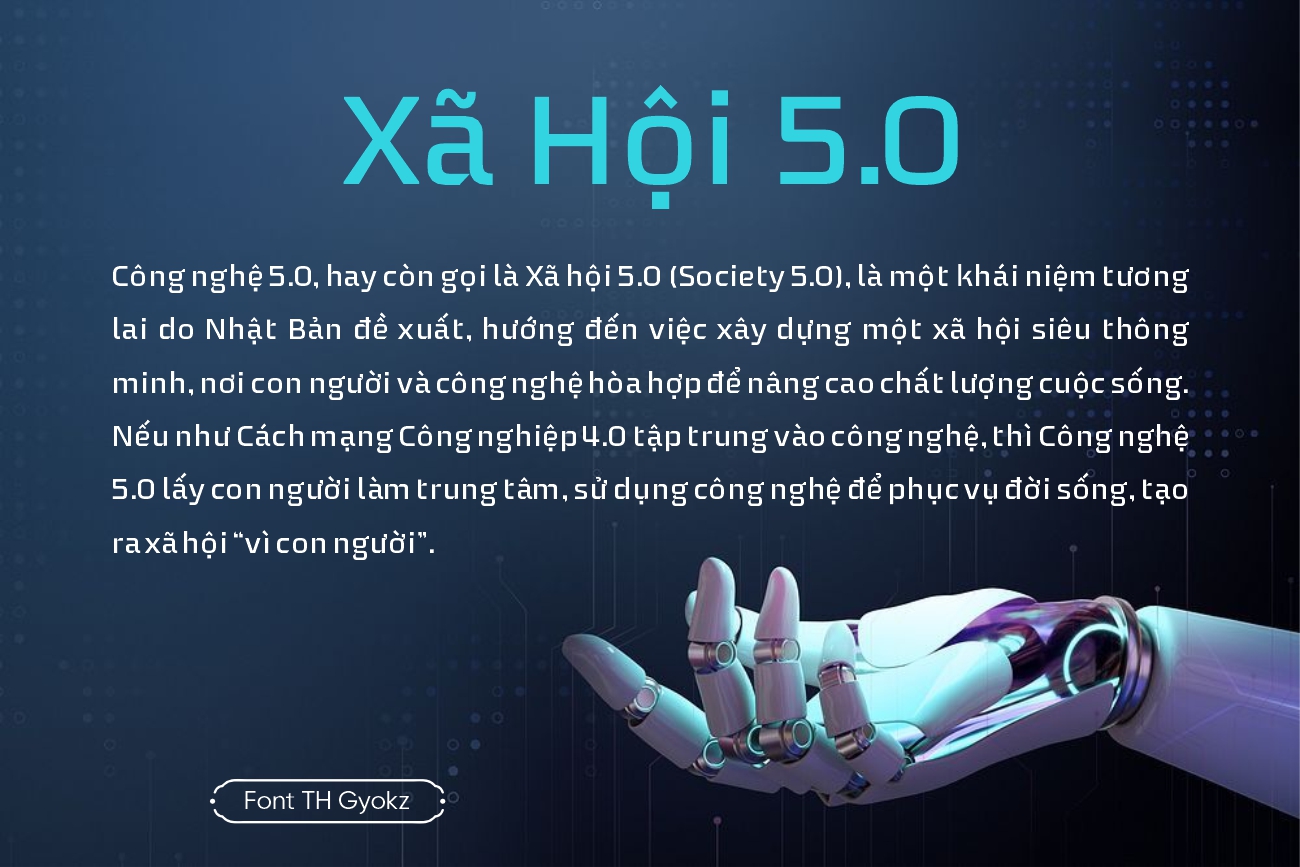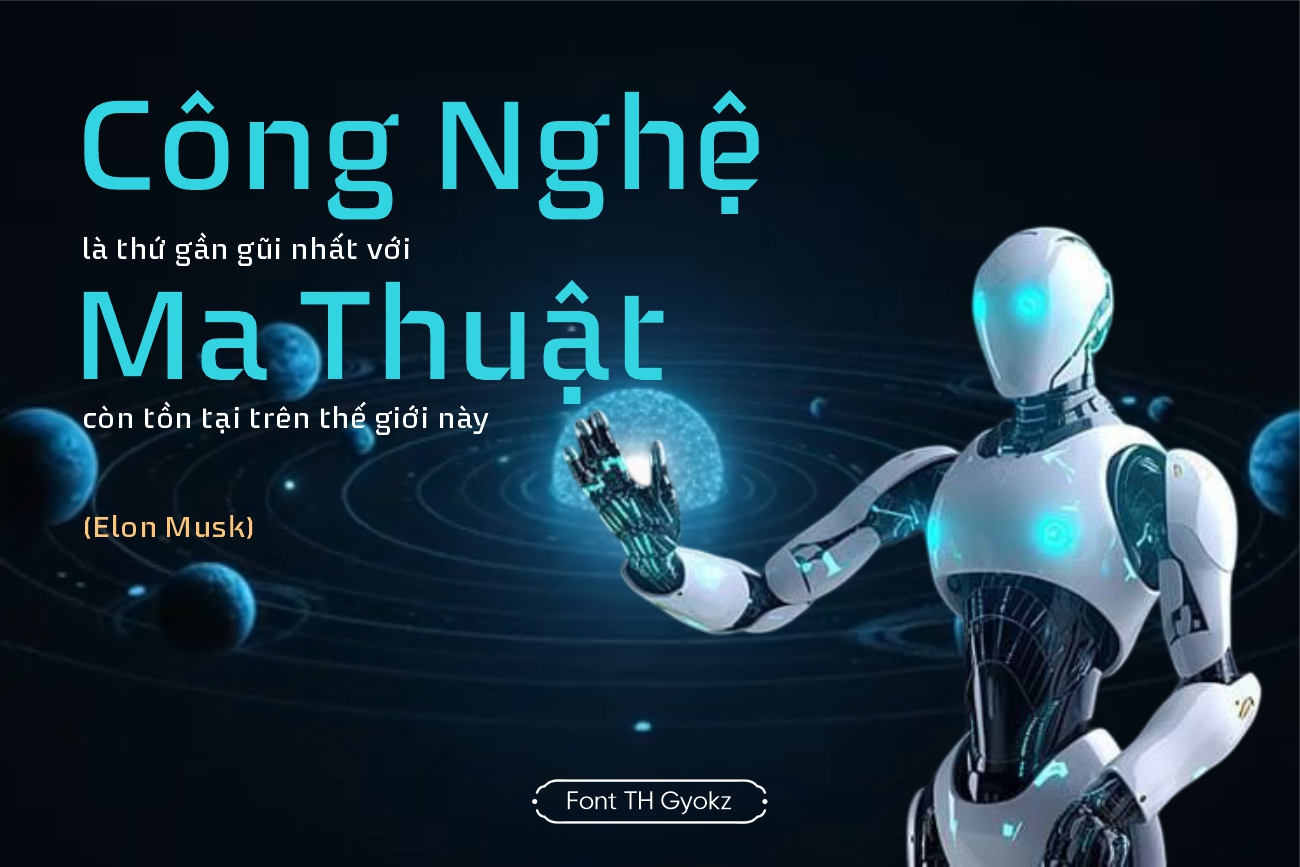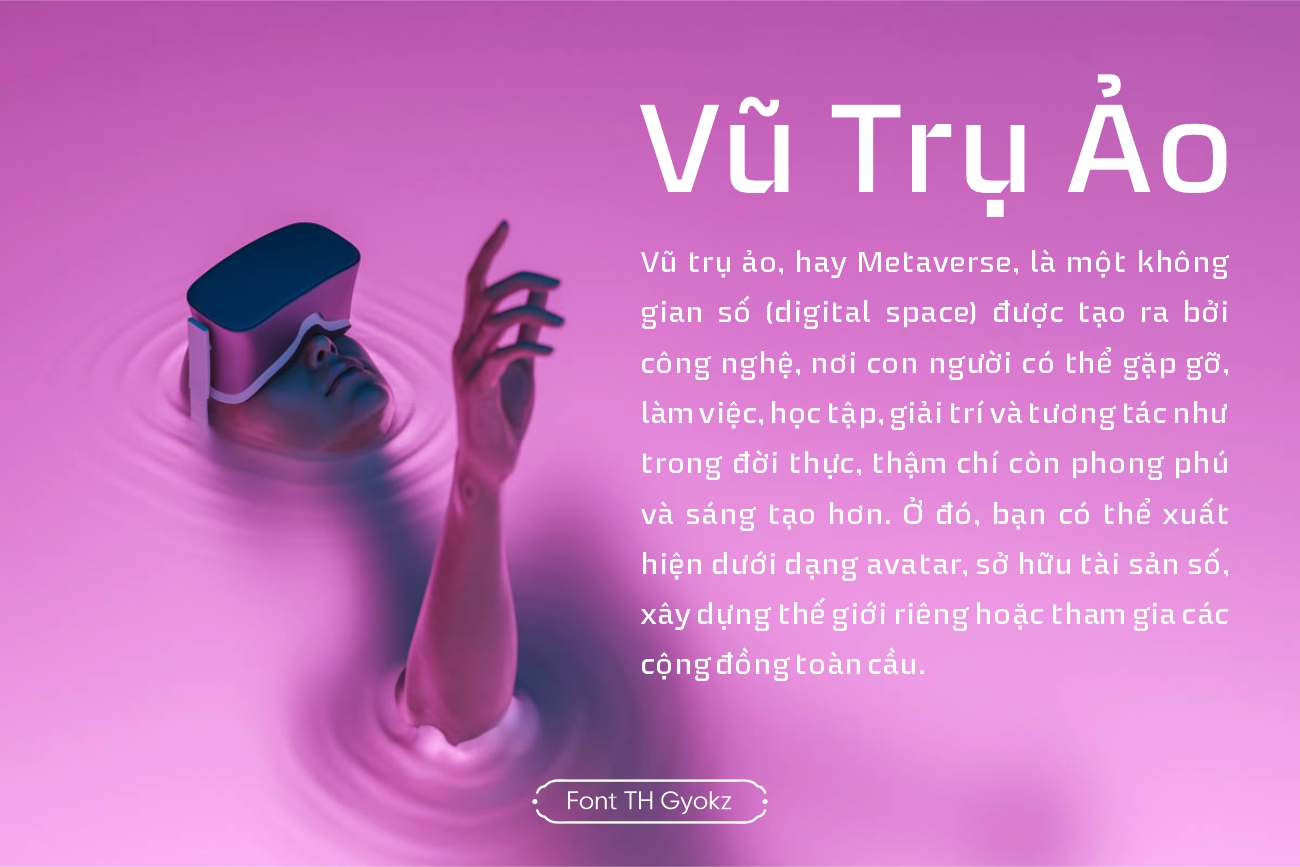
Font Chữ Công Nghệ Hiện Đại TH Gyokz Việt Hóa
Giới thiệu font chữ TH Gyokz
Trong thế giới thiết kế đồ họa không ngừng chuyển mình của kỷ nguyên số, việc tìm kiếm một font chữ công nghệ vừa mang hơi thở tương lai, vừa giữ được sự tinh tế cần thiết luôn là bài toán khó với nhiều Designer. Không còn gói gọn trong những nét vẽ khô khan hay cứng nhắc của máy móc, xu hướng typography hiện đại đòi hỏi sự linh hoạt và cảm xúc hơn. Chính vì lý do đó, Gyokz Sans xuất hiện như một chuẩn mực mới, và phiên bản Việt hóa hoàn chỉnh bởi Team TH đã chính thức đưa bộ font này trở thành công cụ đắc lực cho cộng đồng sáng tạo Việt Nam.
Gyokz Sans không phô trương sự hầm hố thường thấy ở các kiểu chữ điện tử truyền thống. Thay vào đó, nó sở hữu vẻ đẹp của sự "tự tin tĩnh lặng", được kết hợp khéo léo giữa cấu trúc hình học gãy gọn và những tỷ lệ nhân trắc học mềm mại. Sự cân bằng độc đáo này giúp nó trở thành một mẫu font chữ công nghệ lý tưởng, phù hợp hoàn hảo cho các dự án liên quan đến trí tuệ nhân tạo, blockchain, fintech hay các startup kỹ thuật số. Dù hiển thị trên giao diện website, ứng dụng mobile (UI/UX) hay các poster quảng cáo khổ lớn, Gyokz Sans đều mang lại cảm giác hiện đại, sạch sẽ và cực kỳ chuyên nghiệp.
Điểm mạnh của bộ font này nằm ở hệ thống 7 độ đậm nhạt khác nhau, từ nét mảnh mai thanh lịch đến nét đậm đầy quyền lực, giúp người thiết kế dễ dàng tạo ra độ tương phản ấn tượng cho tác phẩm. Đặc biệt, bản Việt hóa do Team TH thực hiện đã giải quyết triệt để vấn đề hiển thị ngôn ngữ. Từng dấu tiếng Việt được chăm chút tỉ mỉ, cân chỉnh khoảng cách kỹ lưỡng để đảm bảo dòng chảy văn bản mượt mà nhất mà không phá vỡ kết cấu hình học nguyên bản.
Có thể nói, sự kết hợp giữa tư duy thiết kế futuristic và khả năng hiển thị tiếng Việt chuẩn xác đã biến Gyokz Sans trở thành một "vũ khí" không thể thiếu trong kho tài nguyên của bạn. Nếu bạn đang ấp ủ một dự án branding cần sự đột phá về mặt thị giác, đây chắc chắn là mẫu font chữ công nghệ đáng để trải nghiệm và sở hữu ngay hôm nay.